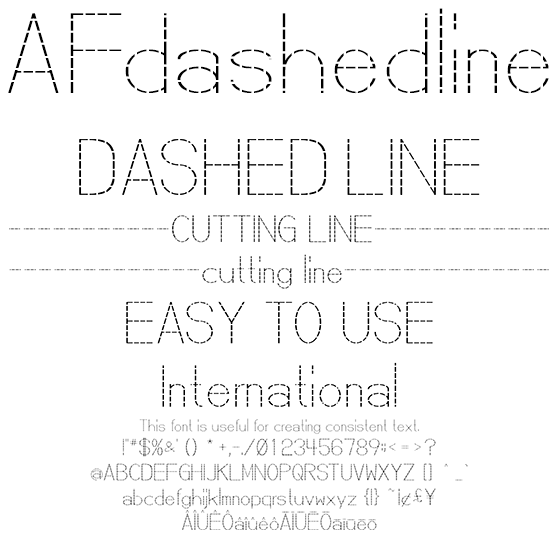
破線欧文 AFdashedline
AFdashedline
破線で作られた極細欧文フォントです。折り紙、型紙、切断などでイメージを強める効果に期待できます。また、破線であることから目視できない形状を表現するコメントで実線やその記載と差異を印象付けられるでしょう。極めて類似性の低い文字デザインであることから、文字サイズを小さくすることで造偽造防止などセキュリティフォントとしてのご利用もご検討ください。